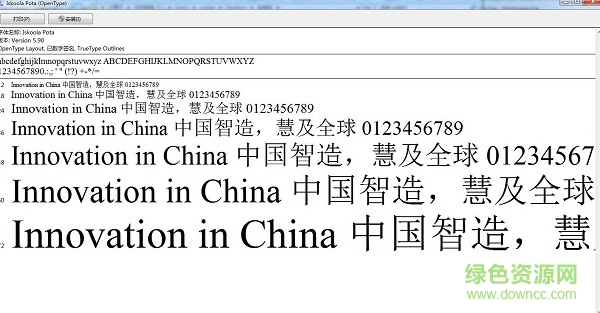
iskoola pota-普通(西方)/bold
iskoola pota是什么字體?這是微軟操作系統(tǒng)附帶的襯線字體,結(jié)構(gòu)平整,筆畫(huà)簡(jiǎn)潔,包括了iskoola pota bold和regular普通(西方)兩種字型,歡迎大家來(lái)綠色資源網(wǎng)免費(fèi)下載!